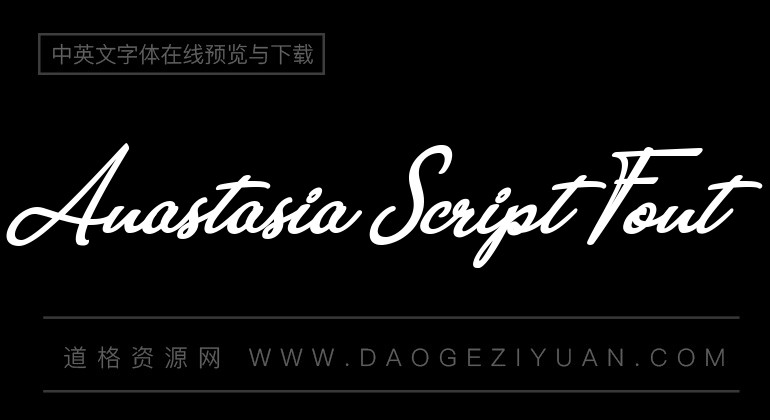
Anastasia Script Font
Anastasia Script Font 是一种充满艺术气息的手写字体,具有优雅、时尚、浪漫的特点。这个字体拥有流畅的连笔和华丽的卷曲特征,是一种非常适合用于印刷设计、品牌标志、广告、海报等设计作品的字体。 Anastasia Script Font 字体非常易于阅读,但它也非常有个性,可以用于各种情境和目的。这个字体有多种字重和风格,包括粗体、斜体、细体和粗斜体等,因此可以根据具体的设计需求进行选择。 总的来说,Anastasia Script Font 是一种非常优美、非常适合创意设计的字体,可以为你的设计作品增添独特的风格和个性。
Anastasia Script Font是一款非常不错的手写艺术字体,具有很好的视觉感,适合于文化类的宣传设计、商业类品牌的广告和产品包装设计以及个性化文字排版等较多场景。